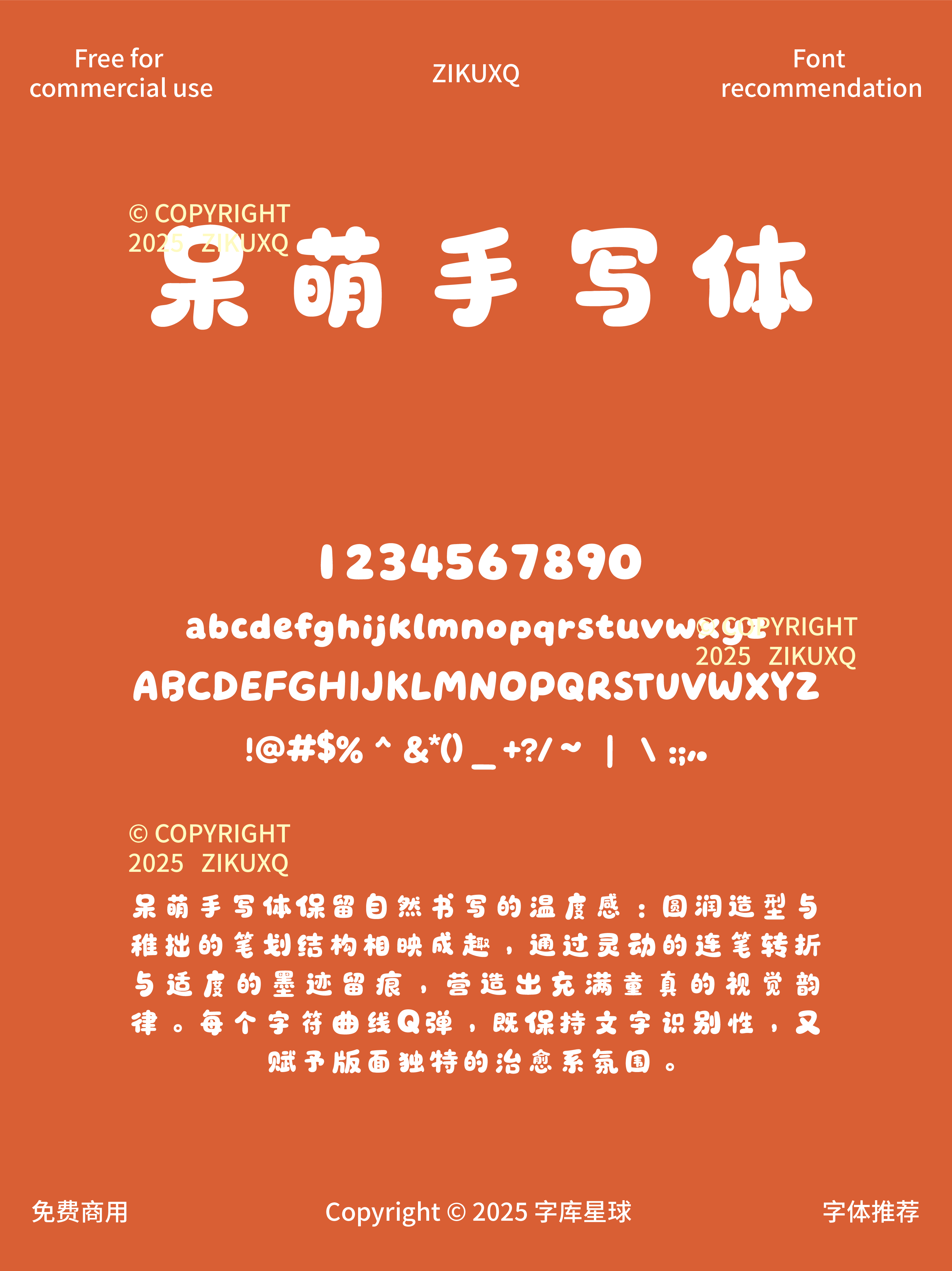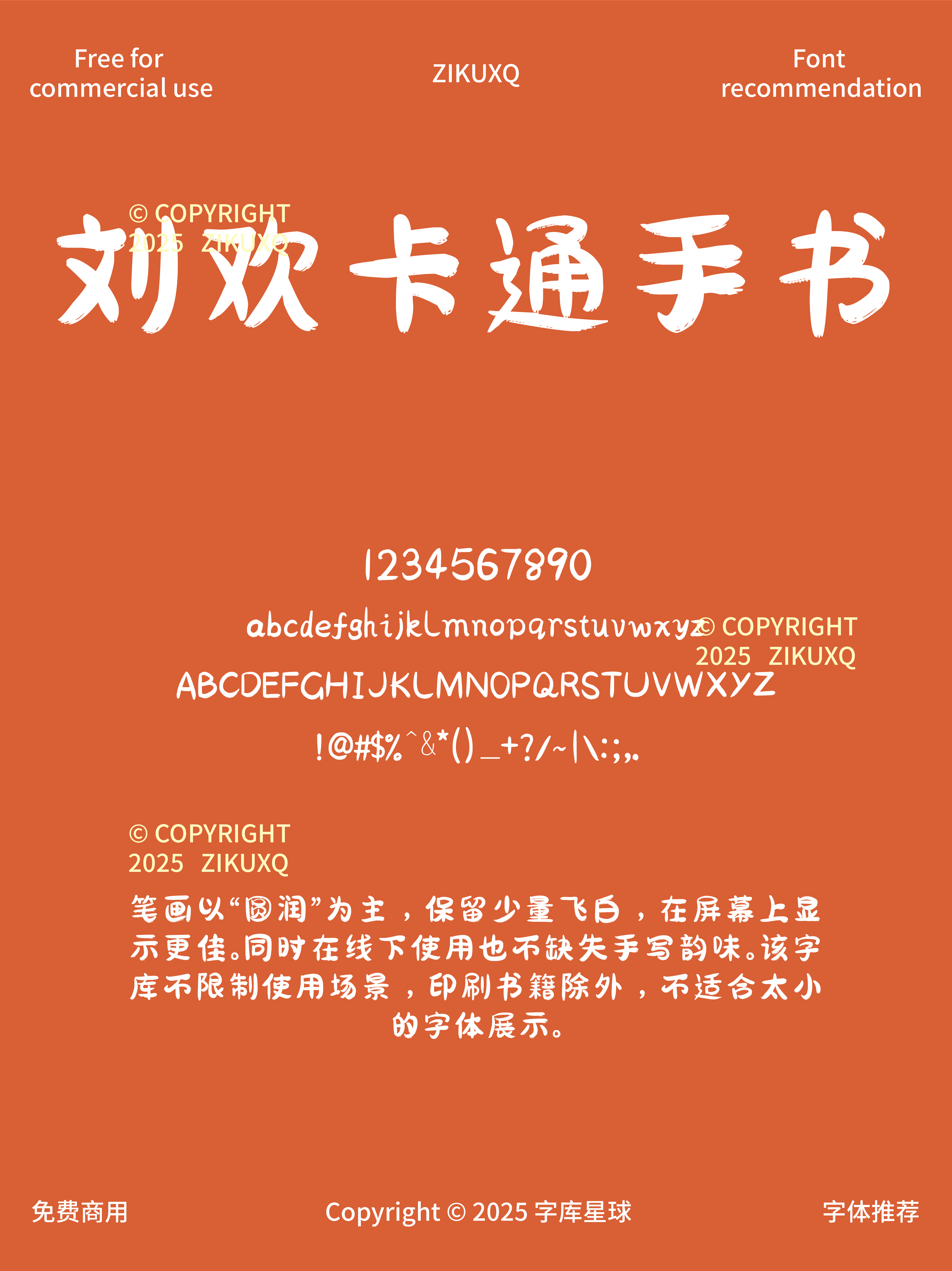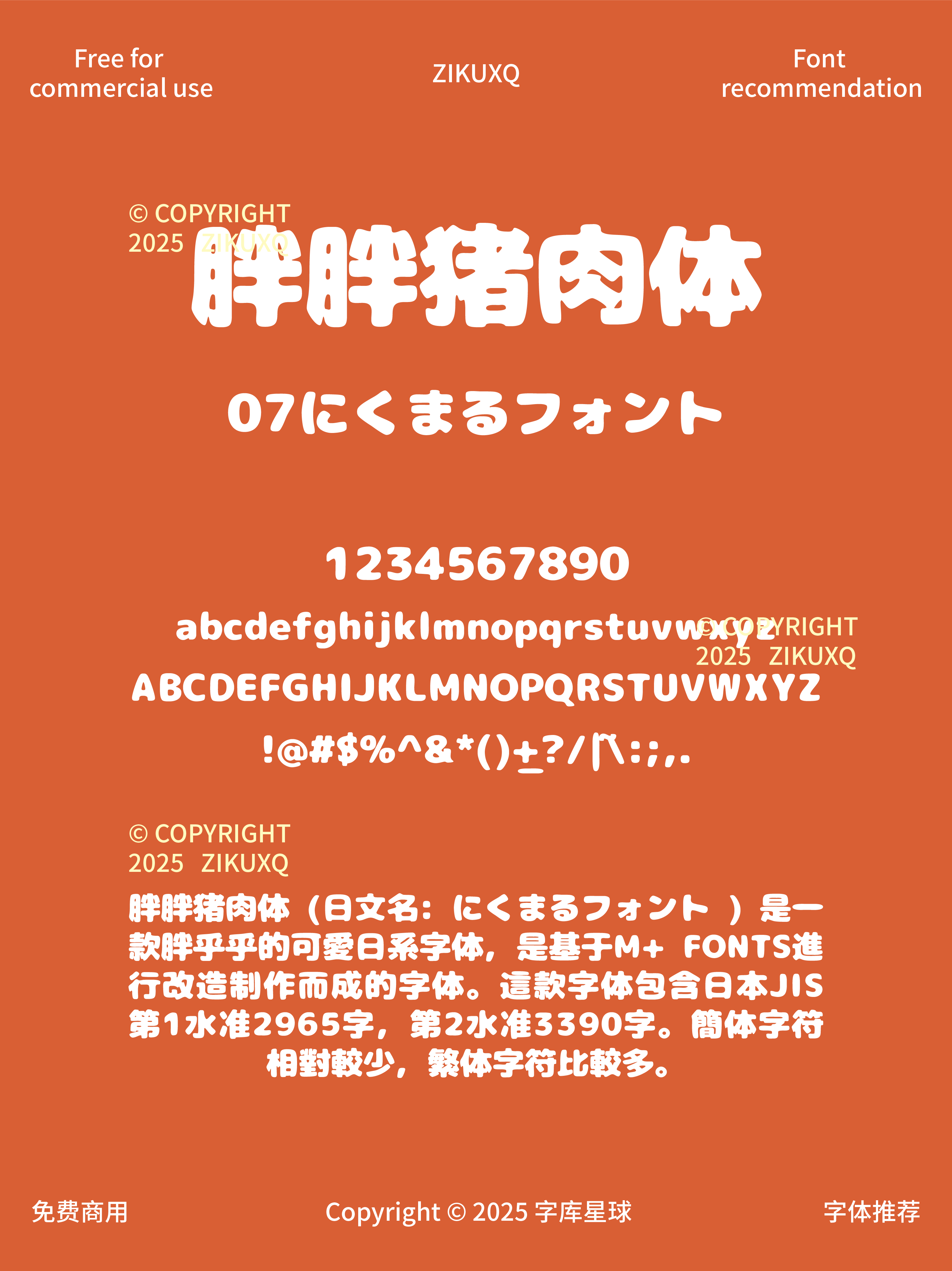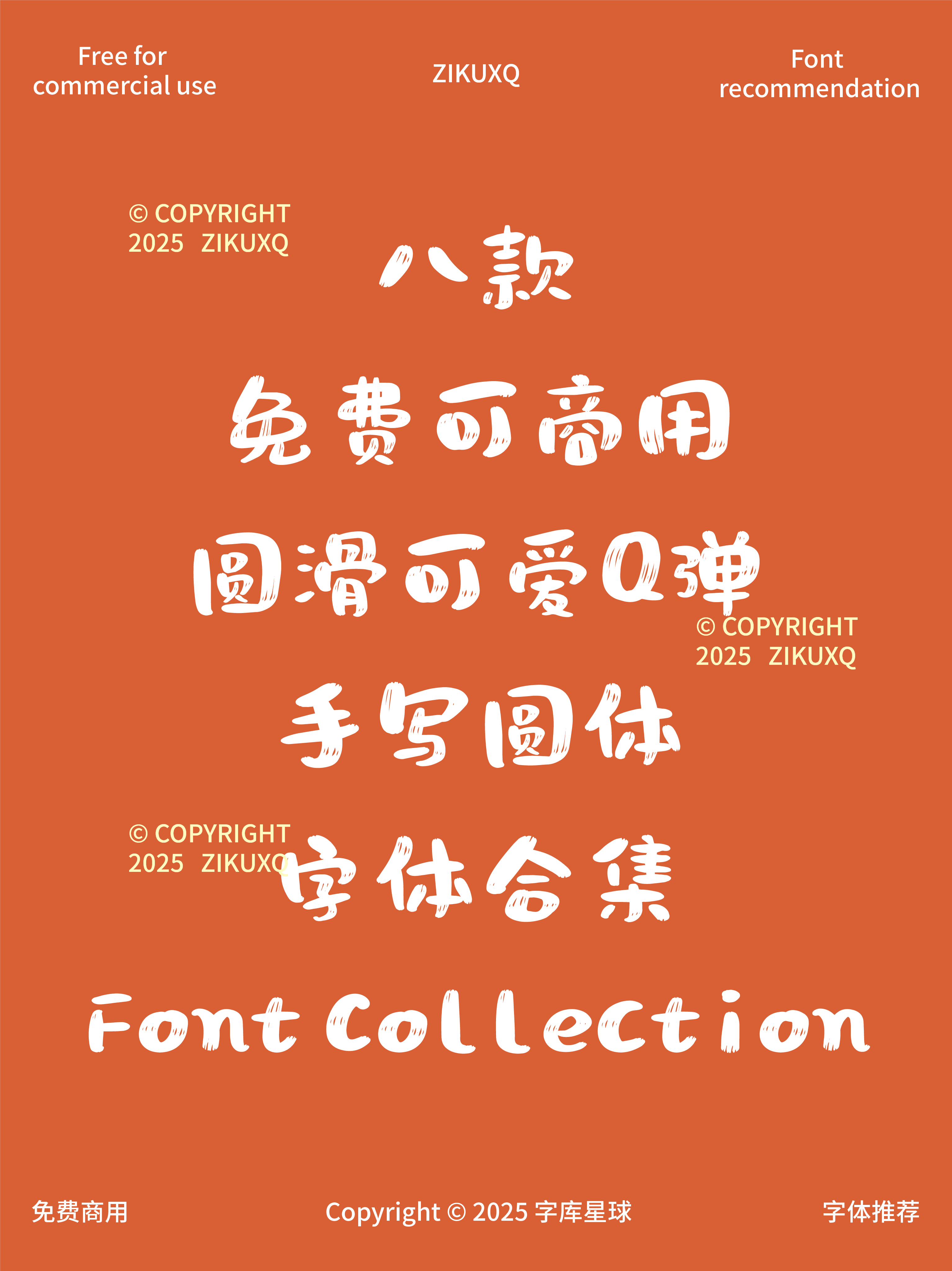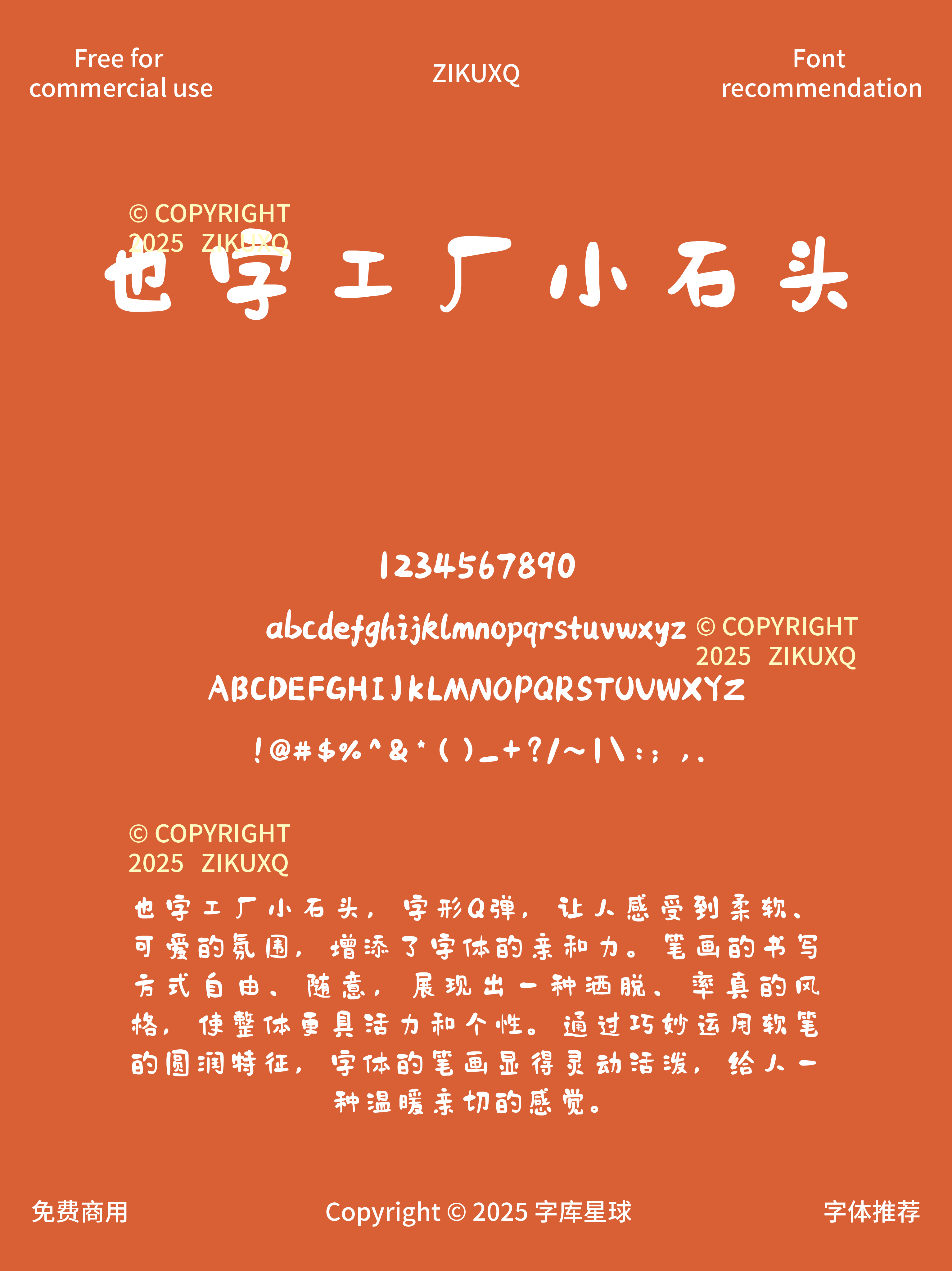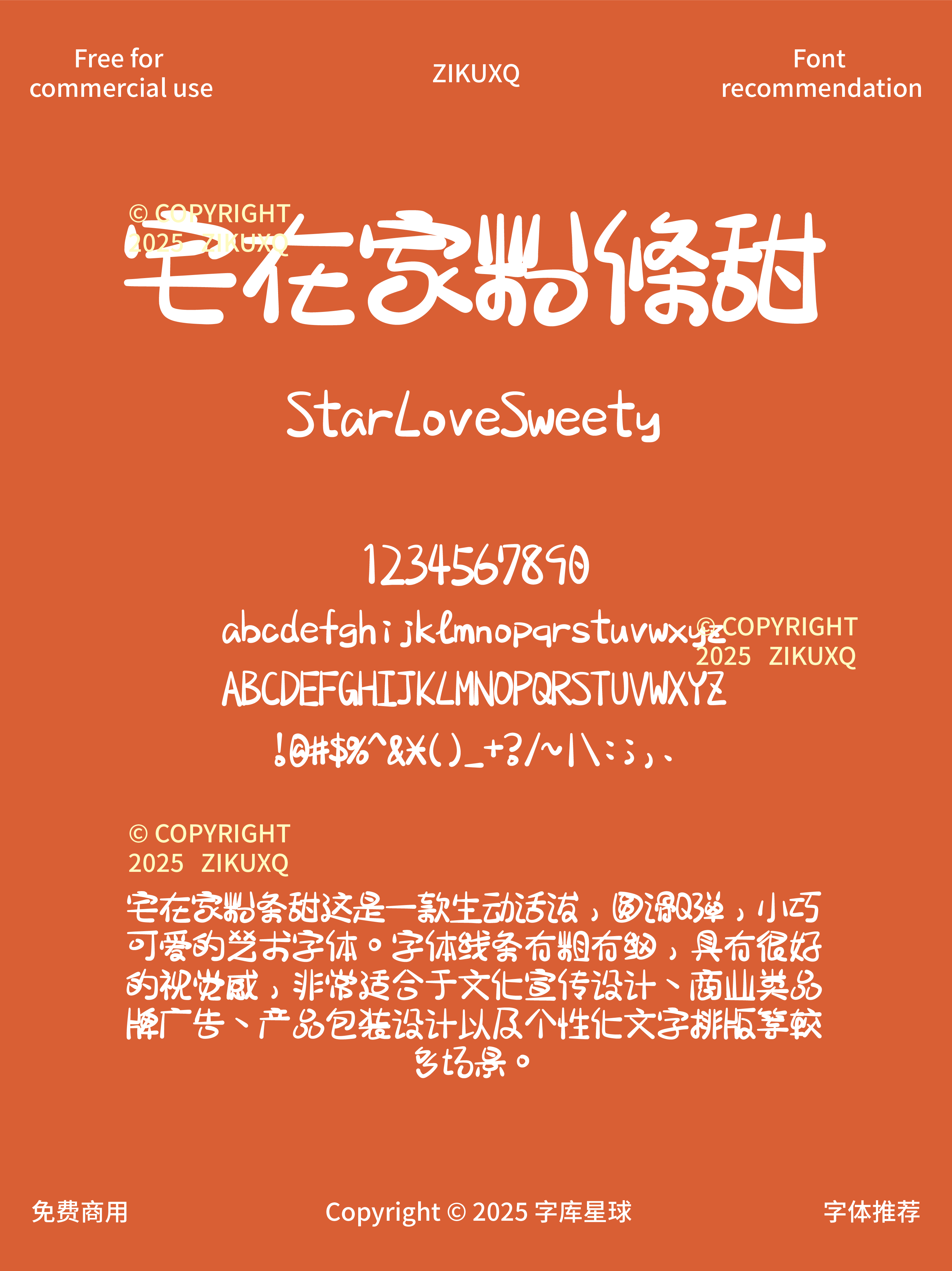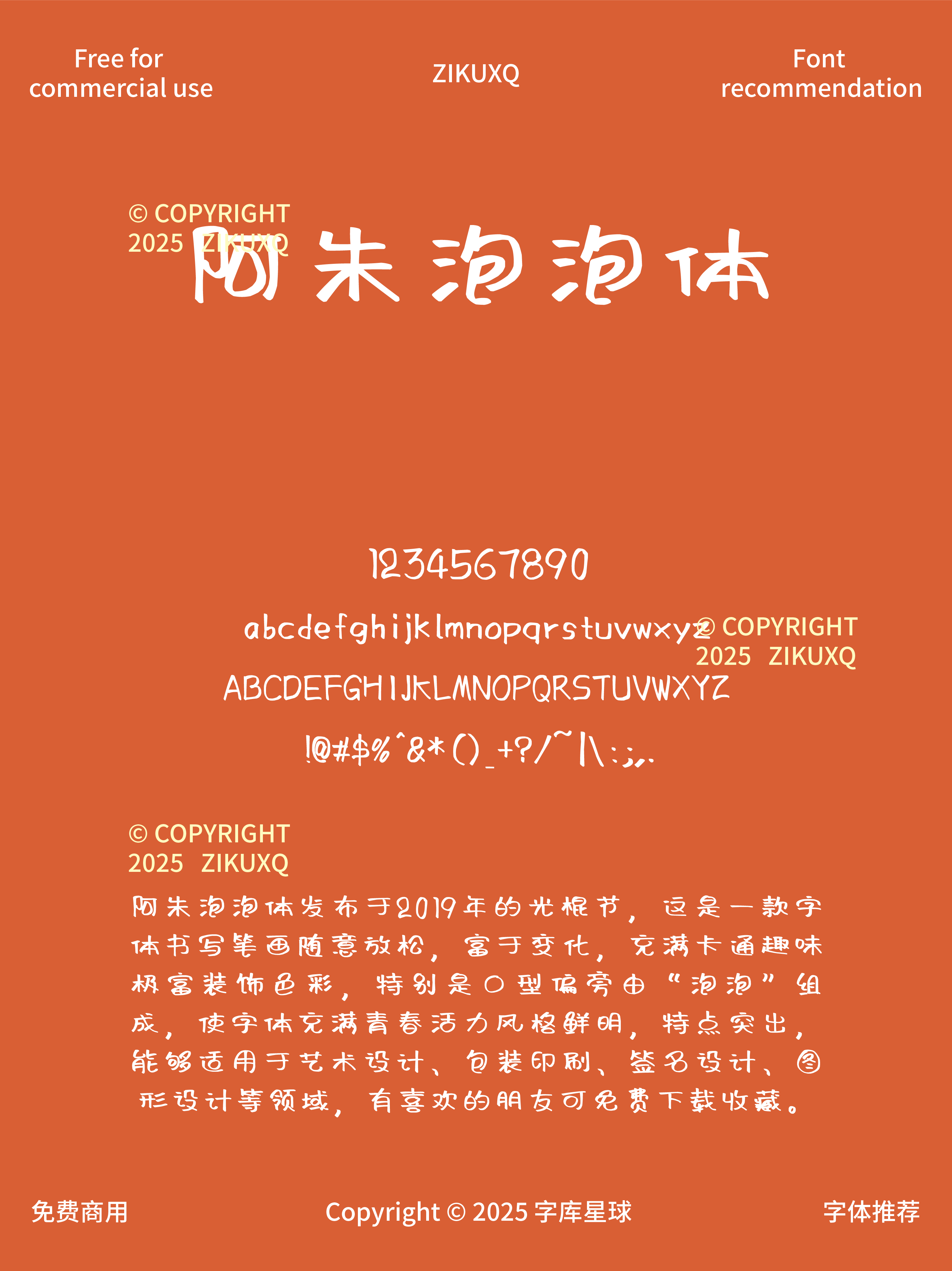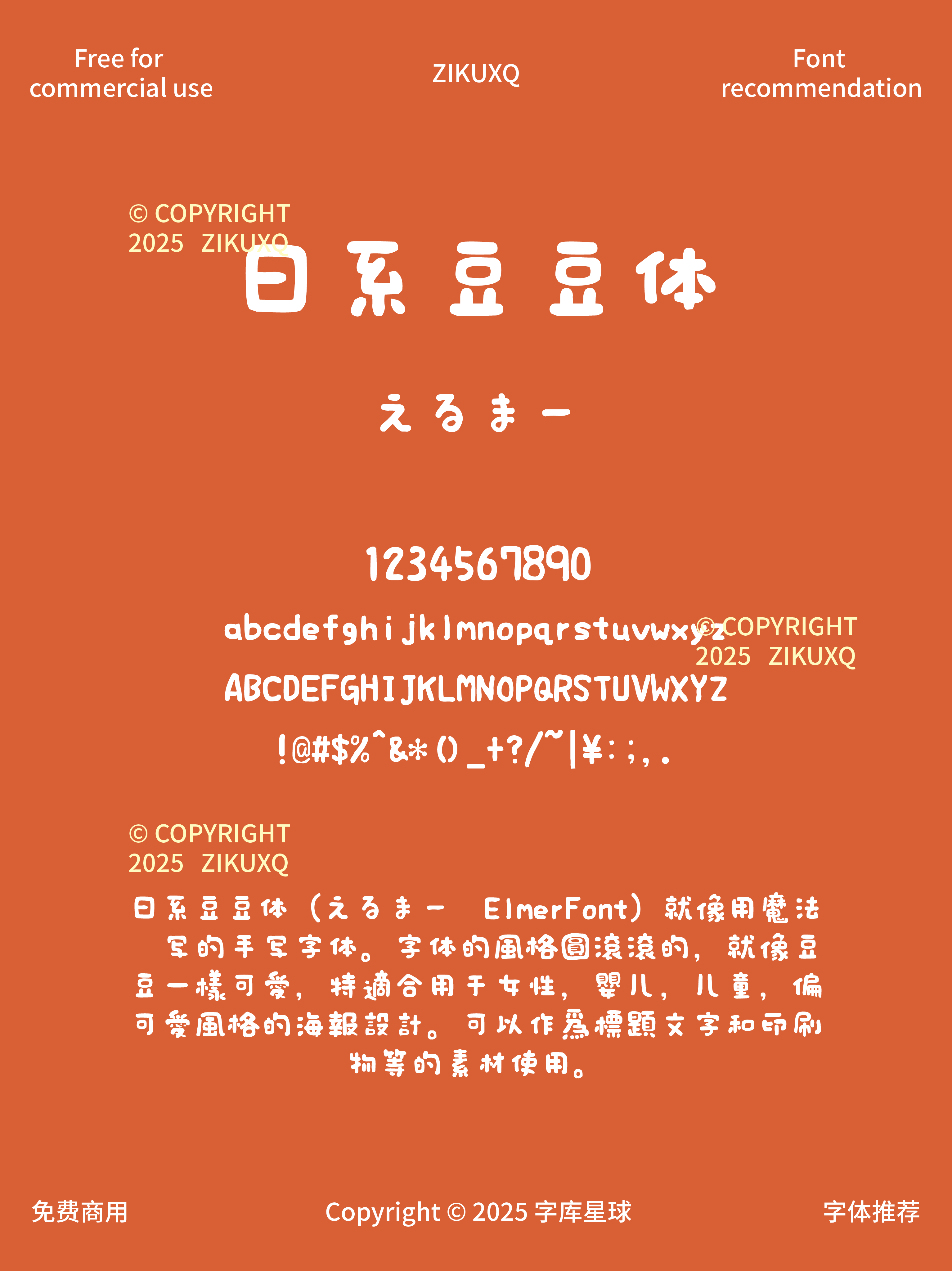
八款免费可商用圆滑可爱Q弹手写圆体字体
还在为找可爱又无版权风险的字体发愁吗?今天挖到 8 款免费可商用的圆滑手写圆体,每一款都 Q 弹到想 rua,设计党速码!
手写感超足的圆体!笔画带点自然的抖动,像小朋友认真写的字,横画末端微微下压,自带亲切感。做亲子活动海报、幼儿园环创,瞬间拉近和观众的距离,字面超级饱满,笔画加粗但不笨拙,竖画收笔像小锤头一样圆润。做零食包装、儿童玩具标签,粗粗的字看着就有安全感,萌得很扎实~